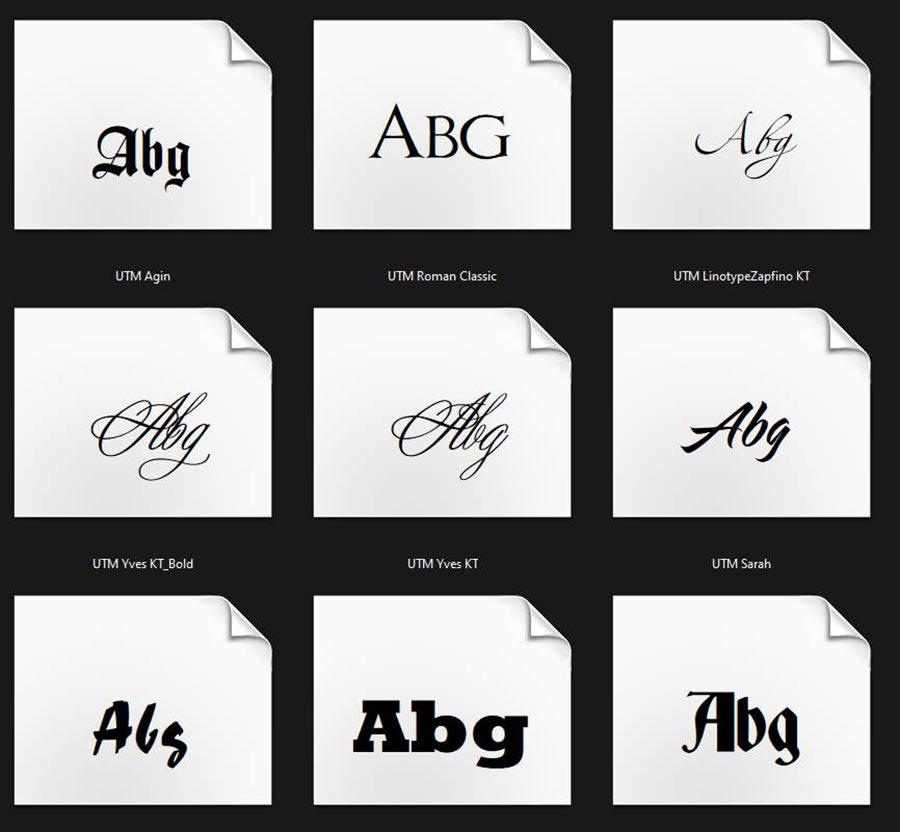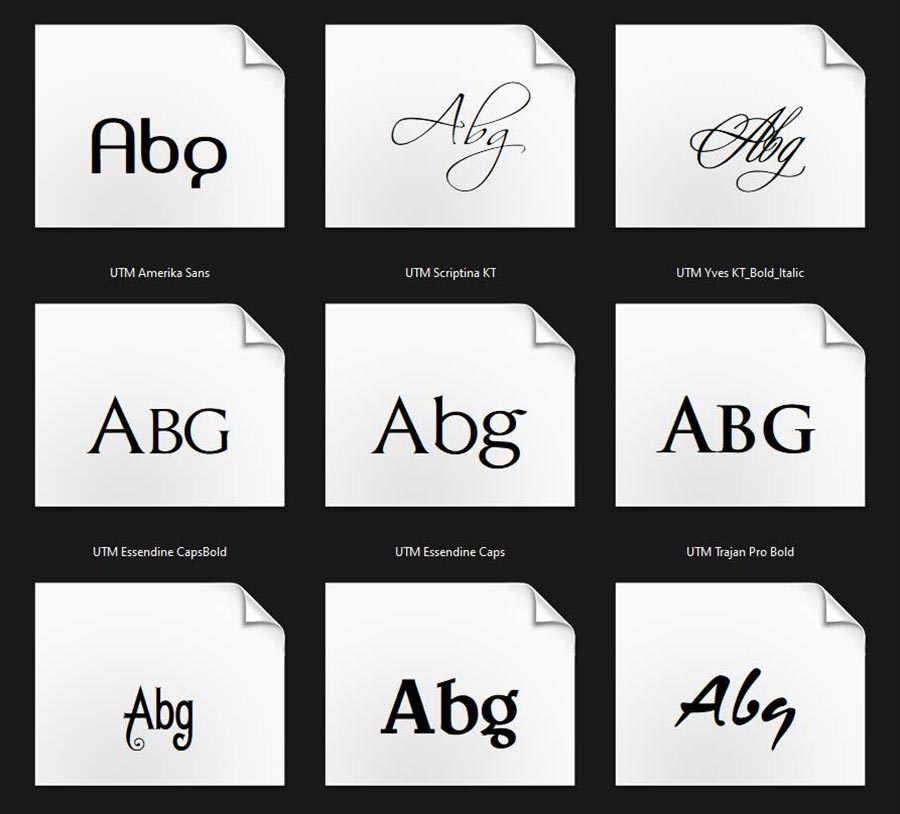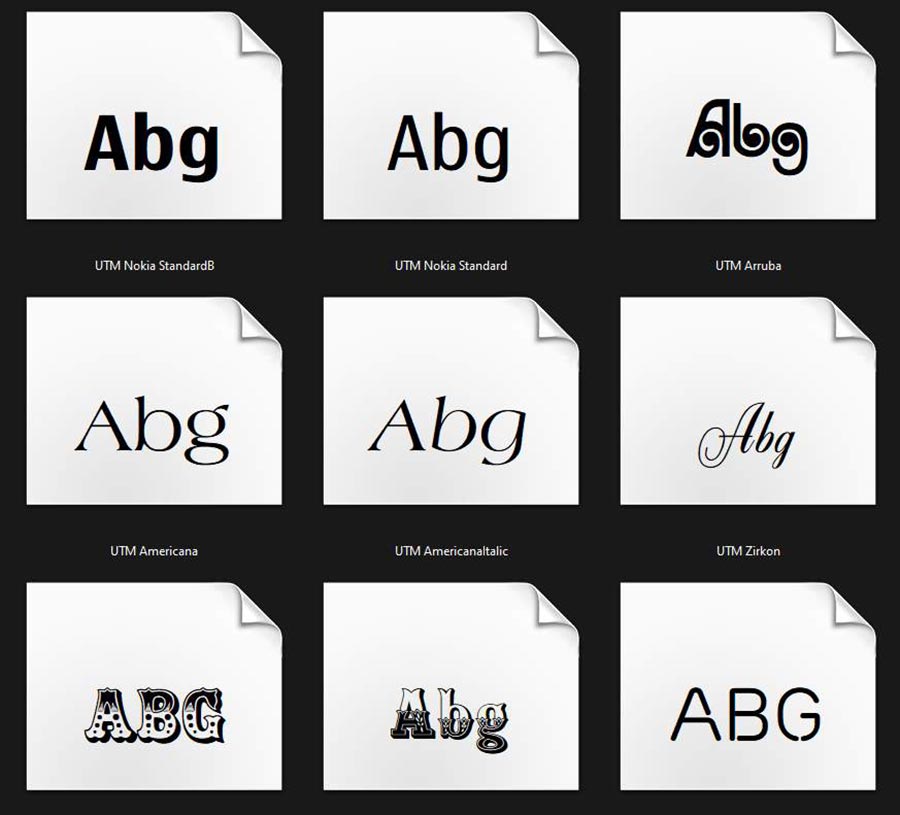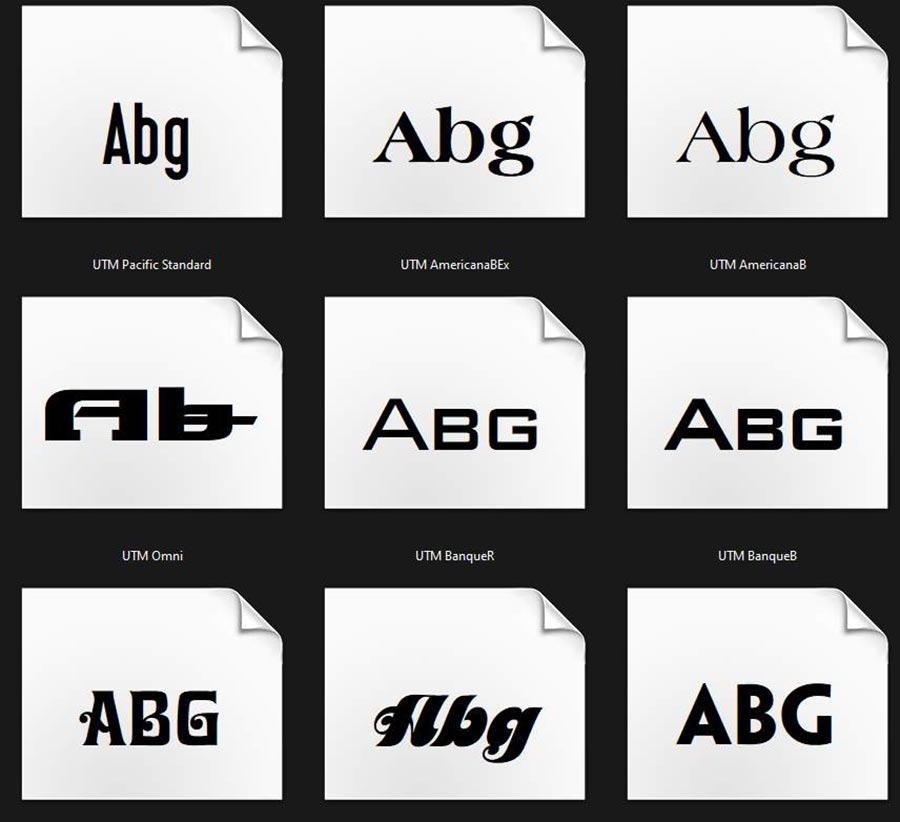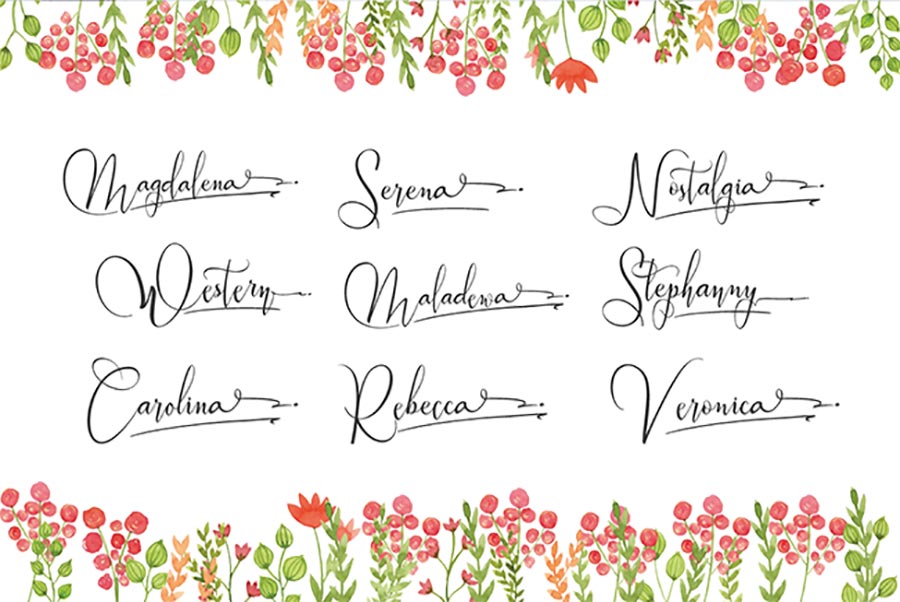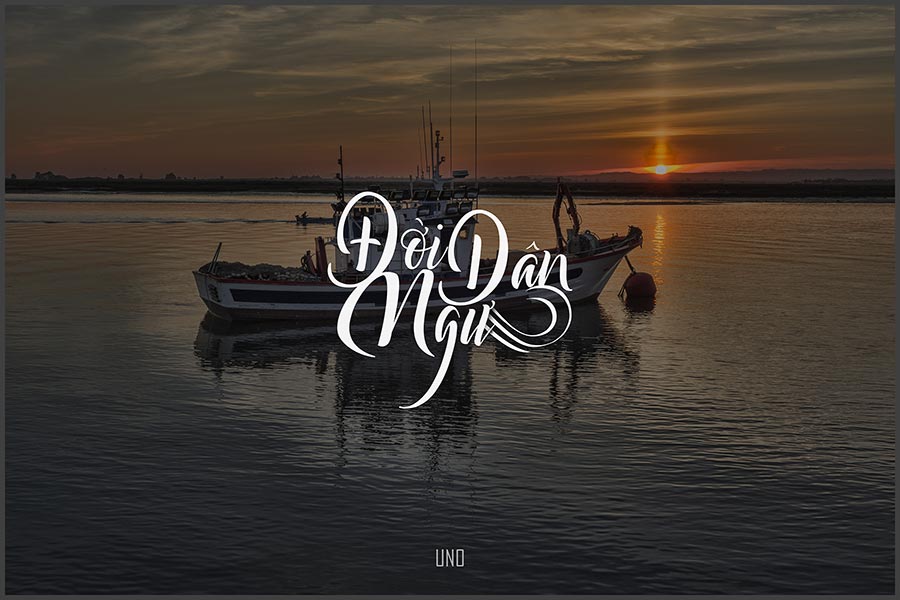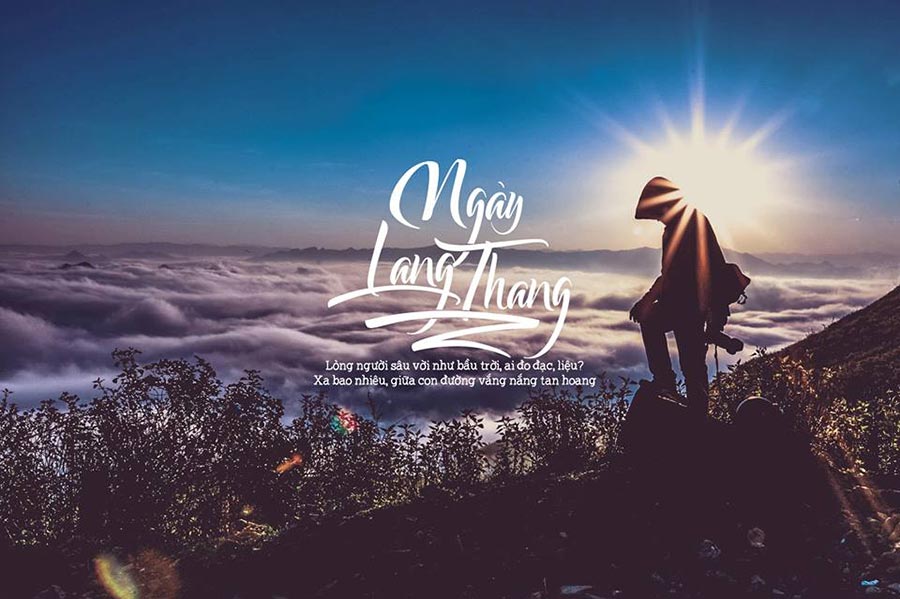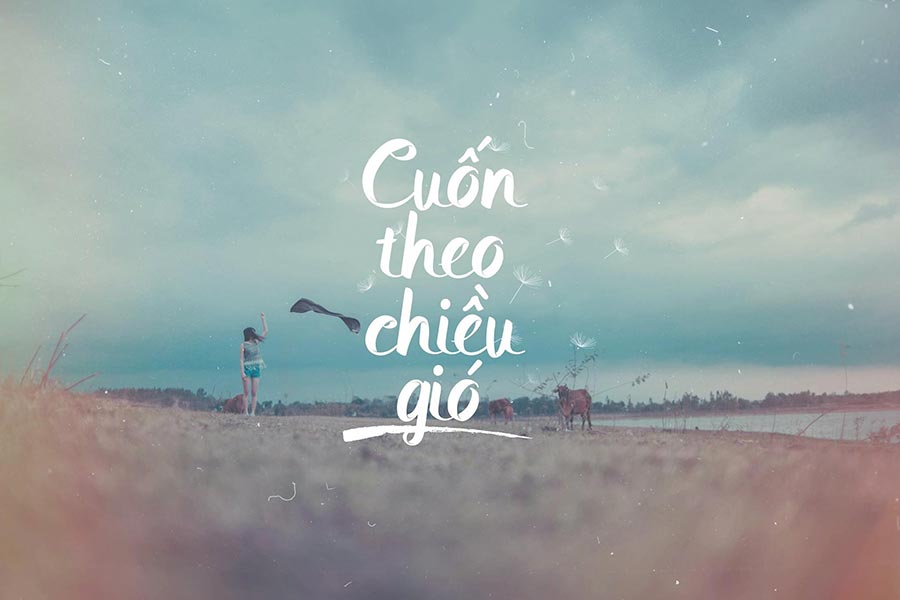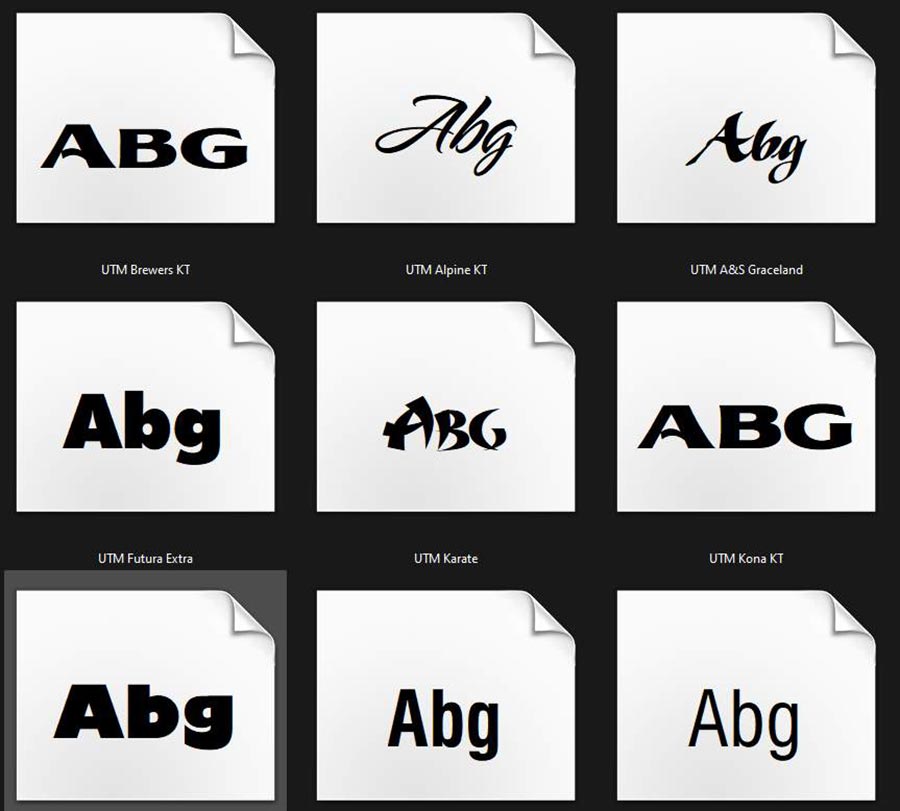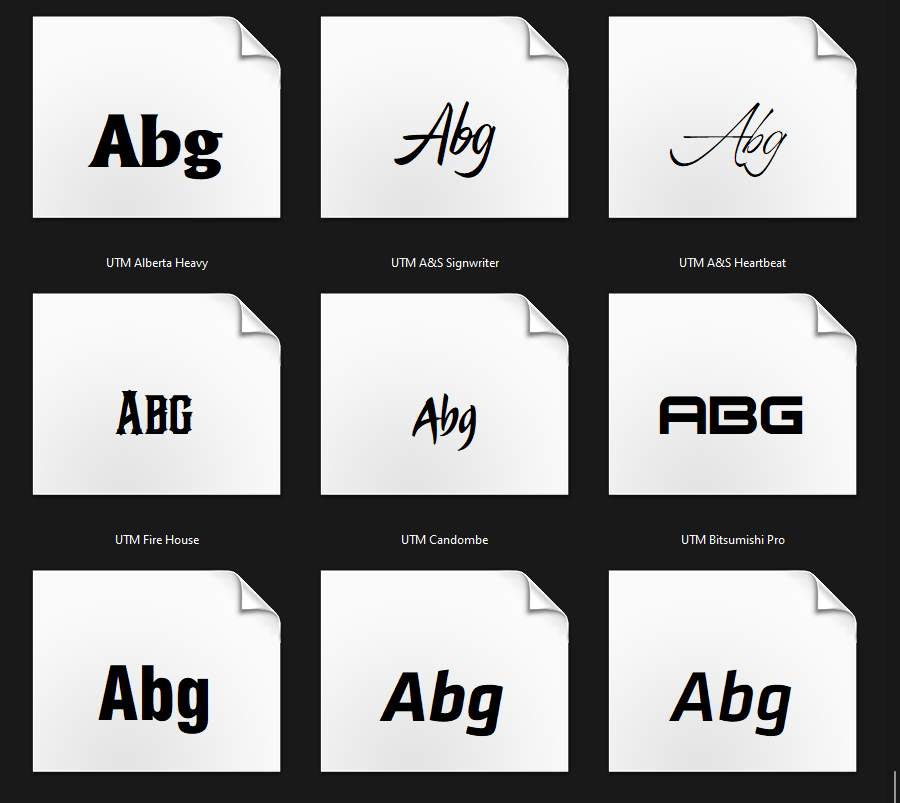
Chia Sẻ Miễn Phí 90+ Bộ Font Đa Dạng Thiết Kế Dành Cho Designer (1)
Font chữ là một trong những yếu tố quan trọng góp phần định hình phong cách và sự chuyên nghiệp của mọi thiết kế. Để hỗ trợ các designer tối ưu hóa quá trình sáng tạo, chúng tôi chia sẻ miễn phí 90+ bộ font độc đáo, từ cổ điển đến hiện đại, phù hợp với nhiều mục đích sử dụng. Tất cả đều sẵn sàng để bạn tải về và ứng dụng ngay hôm nay.
Tầm Quan Trọng Của Font Trong Thiết Kế
Font chữ không chỉ đơn thuần là một phần của nội dung mà còn góp phần truyền tải cảm xúc, phong cách và thông điệp của thiết kế. Đối với các designer, việc sở hữu bộ font chất lượng giúp:
• Tăng tính thẩm mỹ: Biến các thiết kế đơn giản trở nên sống động.
• Đa dạng phong cách: Tùy chỉnh thiết kế theo xu hướng hoặc yêu cầu cụ thể.
• Tiết kiệm thời gian: Có sẵn font phù hợp để áp dụng ngay lập tức.
Những Ứng Dụng Phổ Biến Của Font Chữ
Bộ font đẹp luôn là điểm nhấn quan trọng trong các dự án như:
• Thiết kế thương hiệu: Logo, danh thiếp, tài liệu marketing.
• In ấn sáng tạo: Tạp chí, thiệp mời, poster.
• Nội dung kỹ thuật số: Website, app, banner quảng cáo.
90+ Bộ Font Miễn Phí: Đáp Ứng Mọi Nhu Cầu Sáng Tạo
1. Phong Cách Đa Dạng
Các bộ font được chọn lọc kỹ lưỡng, đáp ứng mọi phong cách thiết kế:
• Font Serif cổ điển: Thích hợp cho các dự án cần sự tinh tế, sang trọng.
• Font Sans-serif hiện đại: Mang lại cảm giác trẻ trung và sáng tạo.
• Font viết tay: Đầy cảm xúc, phù hợp với các thiết kế mang tính cá nhân.
• Font trang trí: Tạo điểm nhấn ấn tượng trong các dự án đặc biệt.
2. Bộ Font Được Đề Cử
Dưới đây là một số bộ font nổi bật trong danh sách chia sẻ miễn phí:
• Roboto: Hiện đại, dễ đọc, hoàn hảo cho nội dung web và ứng dụng di động.
• Montserrat: Phong cách tối giản, phù hợp với thương hiệu hiện đại.
• Playfair Display: Thanh lịch, lý tưởng cho thiết kế in ấn.
• Dancing Script: Mang phong cách mềm mại, tinh tế.